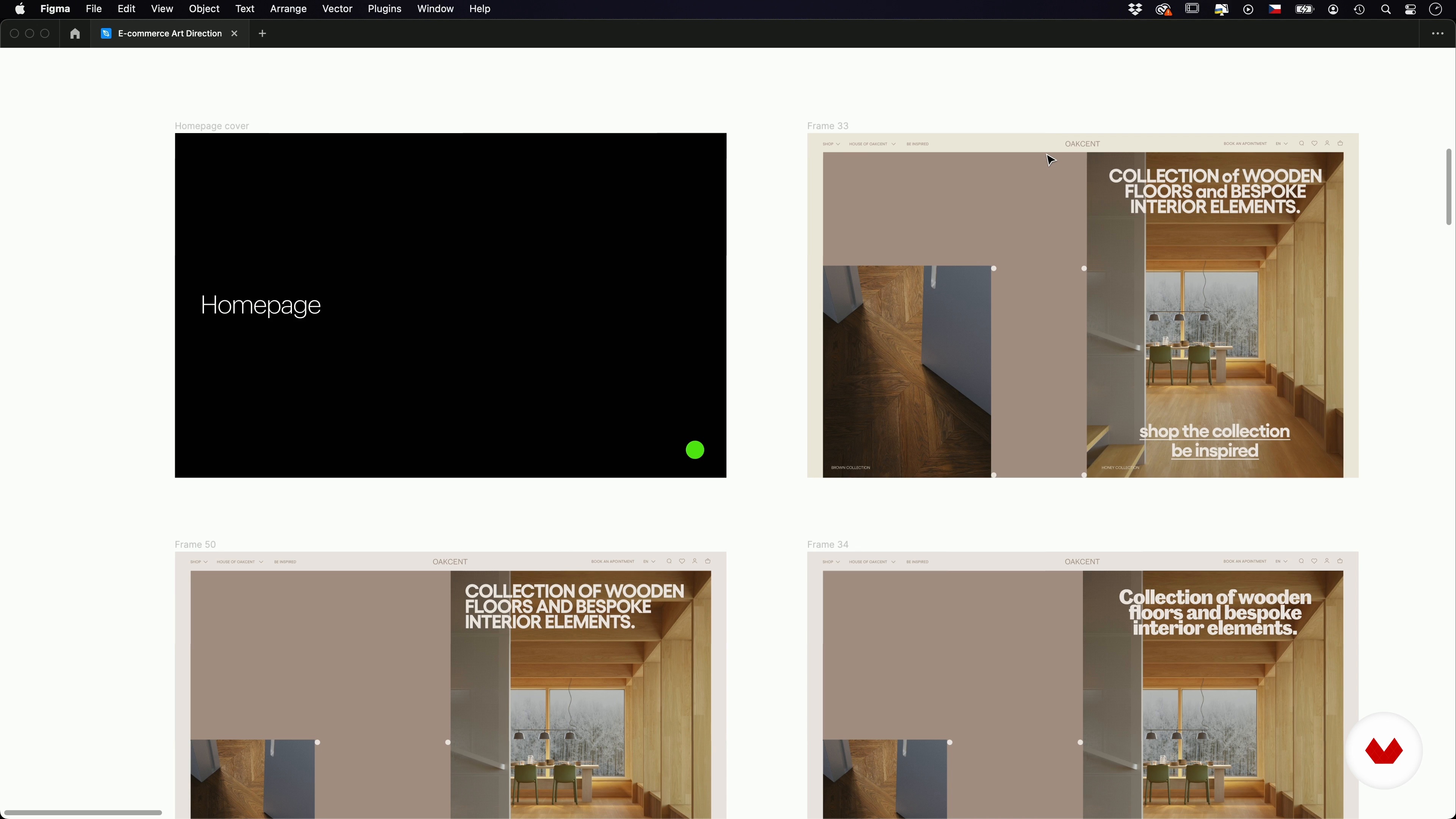
Transmitindo a mensagem com tipografia
Sobre a videoaula: Transmitindo a mensagem com tipografia
“A tipografia tem o poder de moldar a resposta emocional do espectador. As fontes provocam uma reação psicológica que pode ser usada para fazer uma marca parecer mais confiável, amigável ou ambiciosa. Nesta lição, demonstrarei o que considerar para escolher as fontes certas para o seu site. Com minha orientação, você preparará os tamanhos de fonte, hierarquia, contraste, espaçamento entre letras e altura da linha. Por último, mas não menos importante, abordarei temas como consistência, alinhamento, espaço em branco e cor.”
“Transmitindo a mensagem com tipografia O tipo de letra tem o poder de moldar as respostas emocionais de um indivíduo. Fontes provocam uma reação psicológica que podem ser usados para fazer uma marca se sentir mais confiável, amigável, ou aspiracional. Nesta lição, não apenas escolheremos as fontes certas mas também brincaremos com os tamanhos de fonte, hierarquia, contraste, espaçamento entre letras e altura da linha. Por último, mas não menos importante, vamos nos concentrar na consistência, alinhamento, espaço em branco e cor. Vamos dar uma olhada. Trabalhar com fontes costuma ser muito d...”